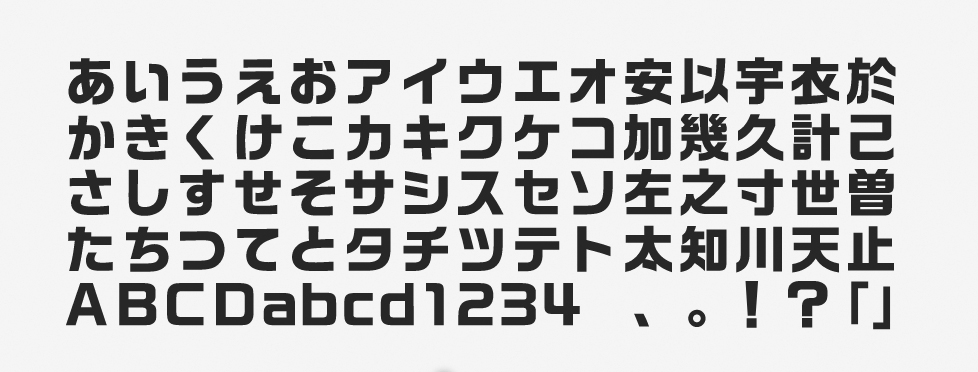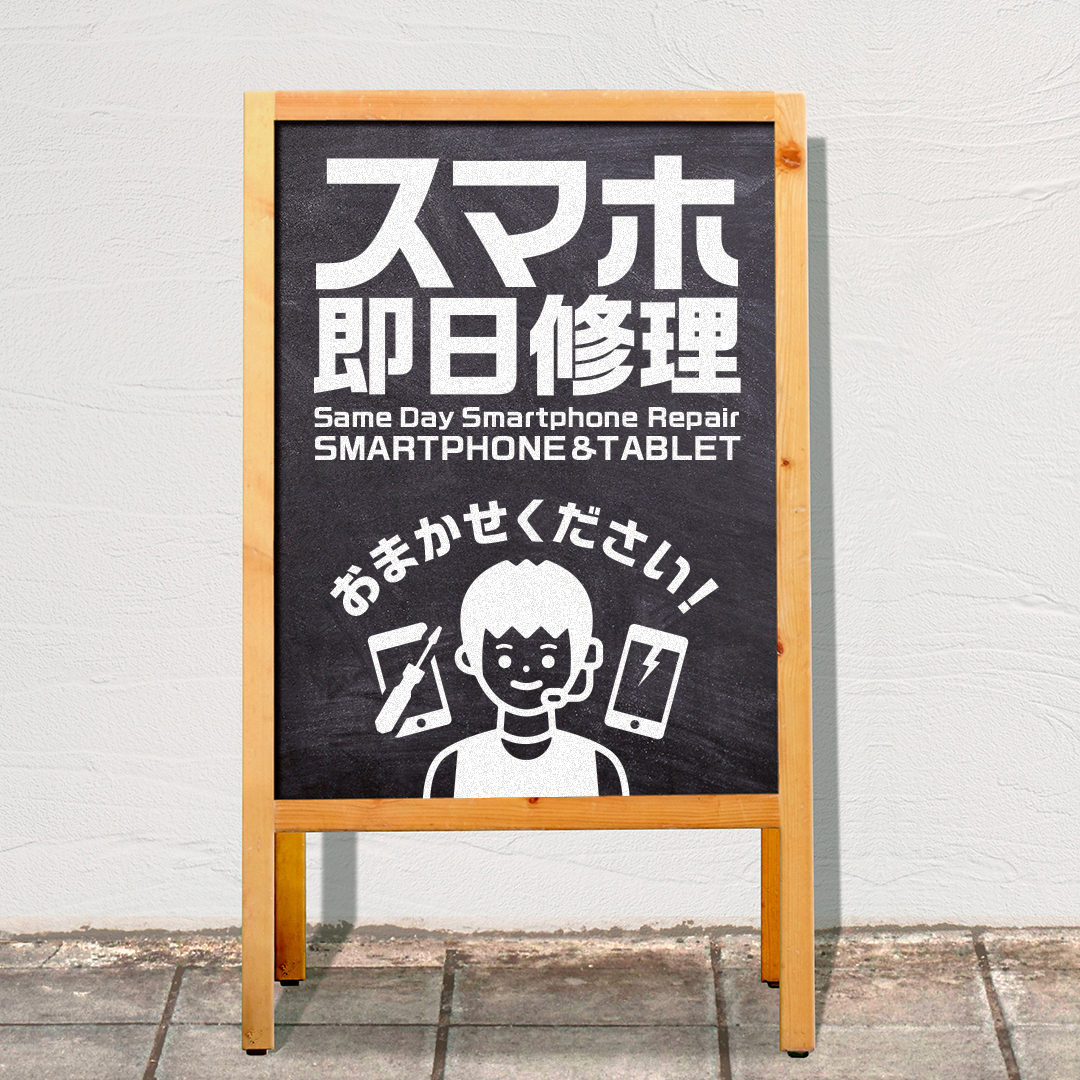
「G2サンセリフ」について
G2サンセリフの名称の「G2」は、もとの書体をデザインした奥泉元晟氏が主宰する「スタジオG2」に由来しています。「サンセリフ」の名前からも分かるように、明朝体のようなセリフ(うろこ)はなく、幾何学的・図形的な印象も備えたおしゃれな書体です。はっきりと読みやすく大きなインパクトを与えます。
「G2サンセリフ」の特徴
それぞれの文字の始筆・終筆の部分は、水平・垂直になるように裁ち落とされています。その処理によって生まれた“ライン”の効果で、縦組みでも横組みでも文字列をすっきり整った印象に仕上げられるフォントです。
しっかりとした力強さがありながらも、読みやすさも両立されています。特に大きな文字サイズで使用されることが多く、ゲームや電子機器などのデジタル的な表現との相性も抜群。見る人を強烈に惹きつけます。
私も過去に何度も何度も助けられきた愛用フォントの1つです。特に漢字、ひらがな、カタカナのデザインが秀逸です。均一な線で表現されたように見えつつ、直線と曲線の取り入れ方が絶妙で、ロゴデザインのベースにすることが多いです。今回の作例のようにカッチリ詰めぎみで組むだけでもロゴらしく表現できます。